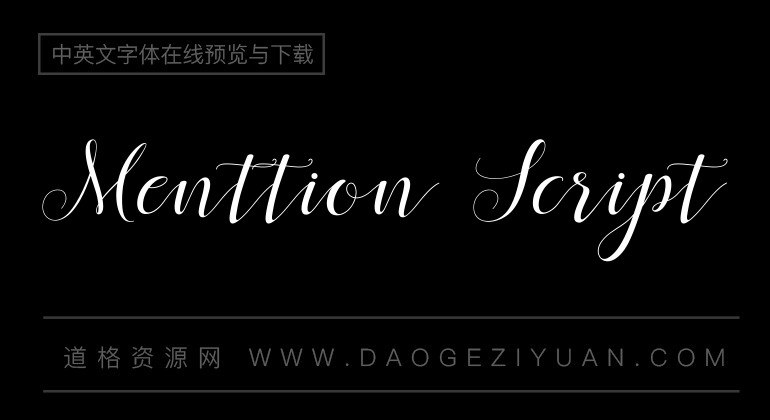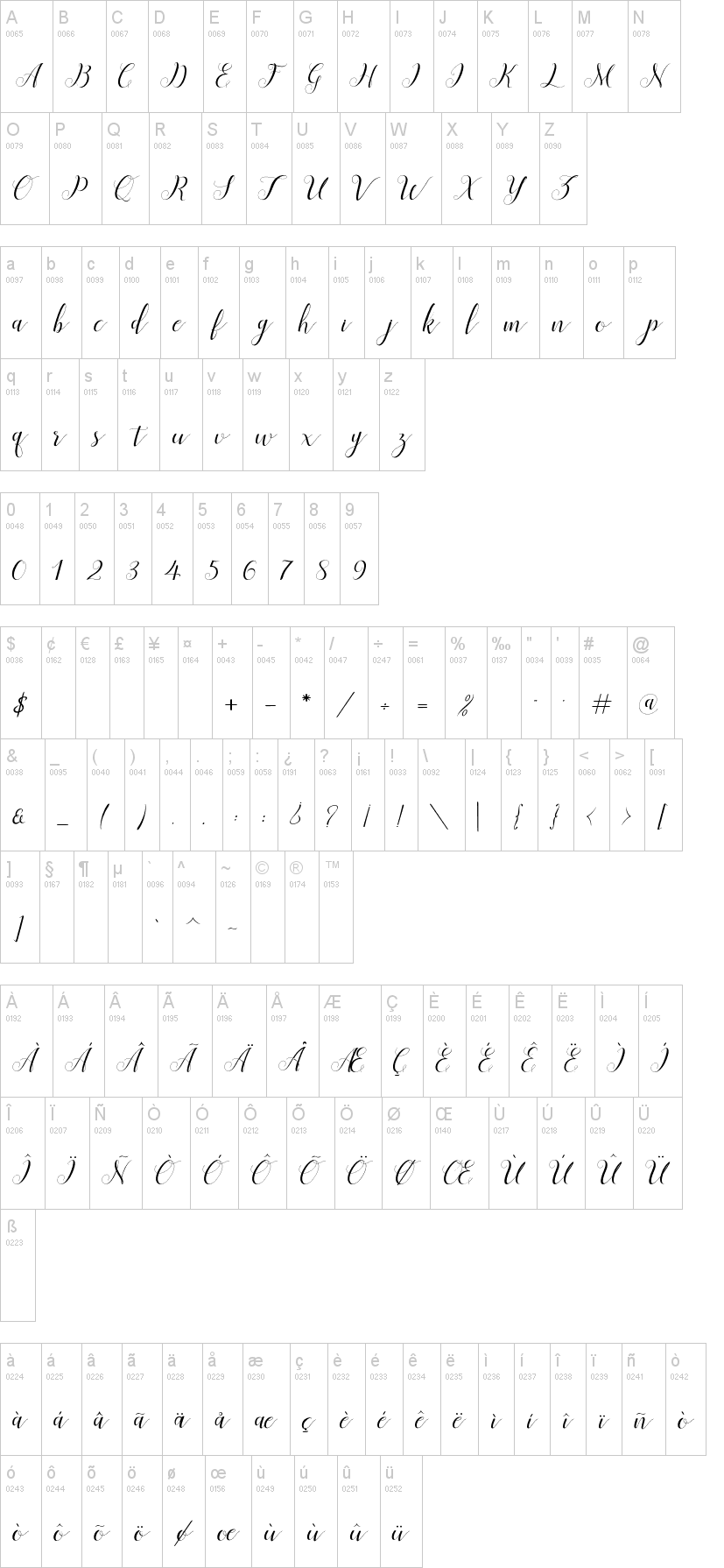
Menttion Script
? Menttion Script 字体是一种手写体字体,它受到了传统西文书法的启发,具有流畅的线条,温暖的气氛,以及多变的字母形状,这使得它非常适合用于日常的文字排版,也可以用来制作浪漫的卡片和海报。它还可以用来制作漂亮的标题和封面,以及各种精美的纪念品。
Menttion Script是一款非常不错的手写艺术字体,具有很好的视觉感,适合于文化类的宣传设计、商业类品牌的广告和产品包装设计以及个性化文字排版等较多场景。
Menttion Script字符映射图